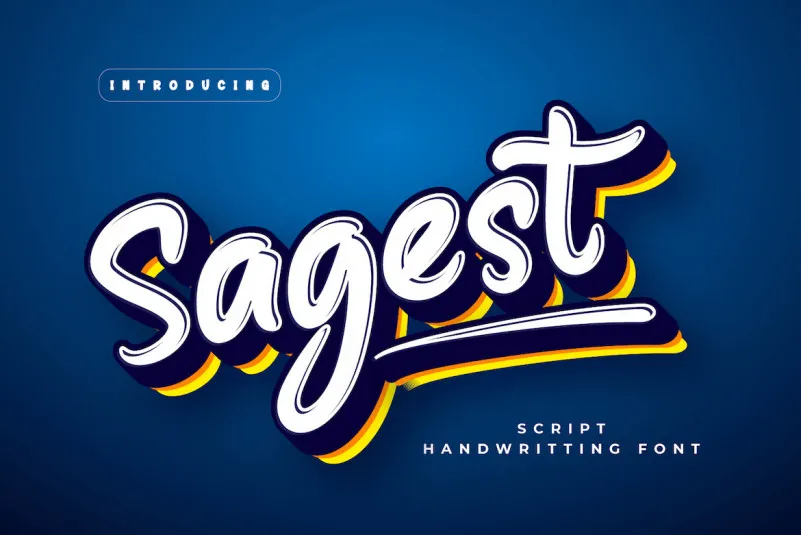
Sagest Font – Download Grátis
A Sagest Font é uma elegante escolha para quem procura um estilo único e sofisticado no design digital. Ela foi criada com a delicadeza de uma mão, trazendo consigo um toque suave e refinado que se destaca em projetos especializados, desde textos até cabeçalhos. A Sagest está concebida para complementar sua marca ou projeto ao dar um toque único e sofisticado. Seja para criar um design atraente para suas redes sociais, para a capa de seu site, ou como parte integrante do layout de uma revista, Sagest traz elegância sem comprometer o impacto visual forte que você deseja projetar. Seja qual for o seu projeto visual, Sagest está aqui para oferecer um toque diferenciado e sofisticado.